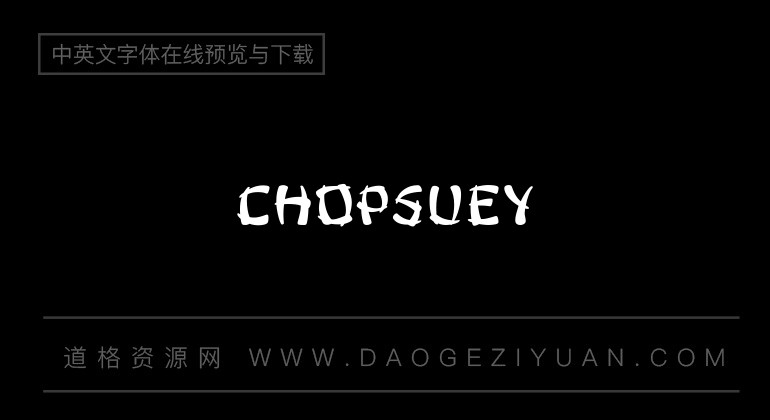
ChopsUey
ChopsUey 字體是一種免費的手寫風格字體,它在設計上結合了傳統手寫風格和現代設計元素,使其看起來既自然又現代化。它的字母和符號都是由手寫筆創作的,因此具有一定的個性和獨特性。此外,ChopsUey 字體也包含了大量的特殊字符和裝飾符號,使其在設計中具有很大的靈活性和創意性。它可用於設計海報、標誌、網站設計、個人名片等等多種設計場景,是一個非常實用的字體選擇。
ChopsUey是一款非常不錯的手寫藝術字體,具有很好的視覺感,適合於文化類的宣傳設計、商業類品牌的廣告和產品包裝設計以及個性化文字排版等較多場景。
ChopsUey字符映射图